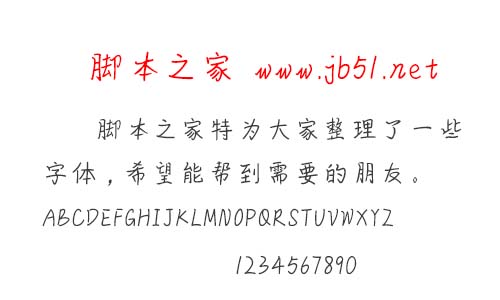
X-童謠手跡是XFont字庫推出的一款常規(guī)簡體中文字體,創(chuàng)作來源就是那些深藏于內(nèi)心的祖孫情,在字體結(jié)構(gòu)上,整體上呈現(xiàn)出來的較簡約,字體呈豎形,這種設(shè)計(jì)正意味著祖父輩簡單又深沉的愛意。設(shè)計(jì)者也想通過這個(gè)字體善意地提醒我們在我們成長過程中要一直都記得那個(gè)唱童謠哄我們?nèi)胨娜?,可?yīng)用于藝術(shù)設(shè)計(jì)、印刷排版等領(lǐng)域。歡迎喜歡X-童謠手跡字體的朋友前來下載使用。